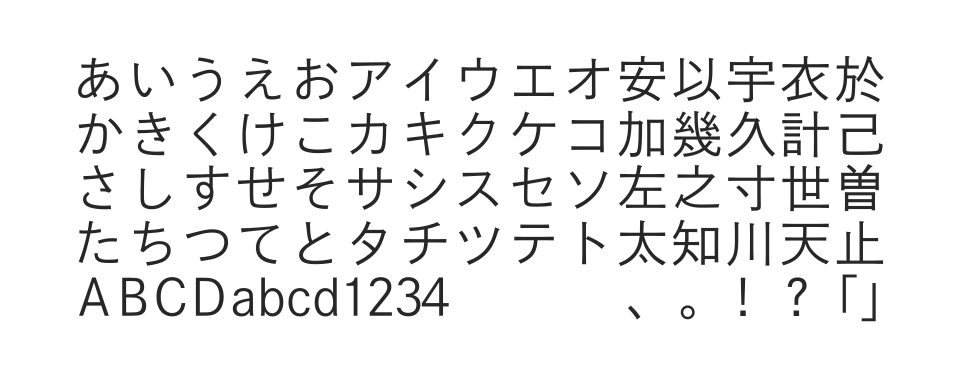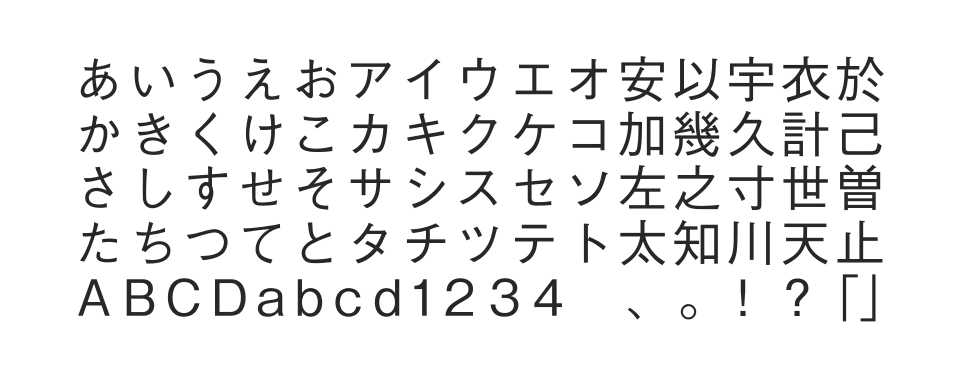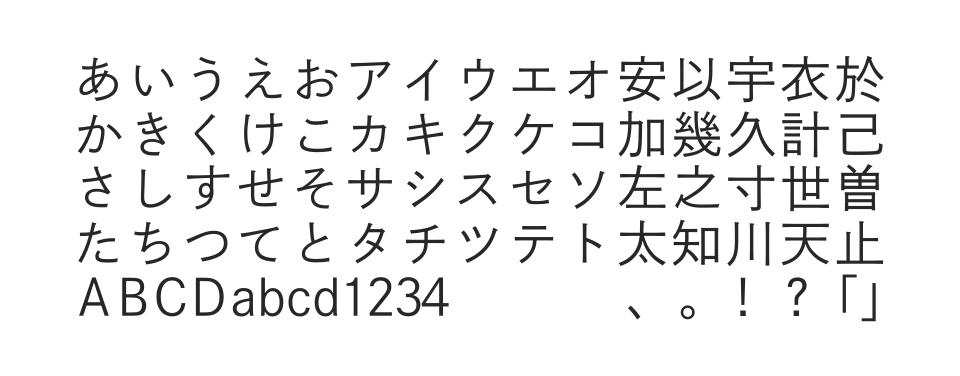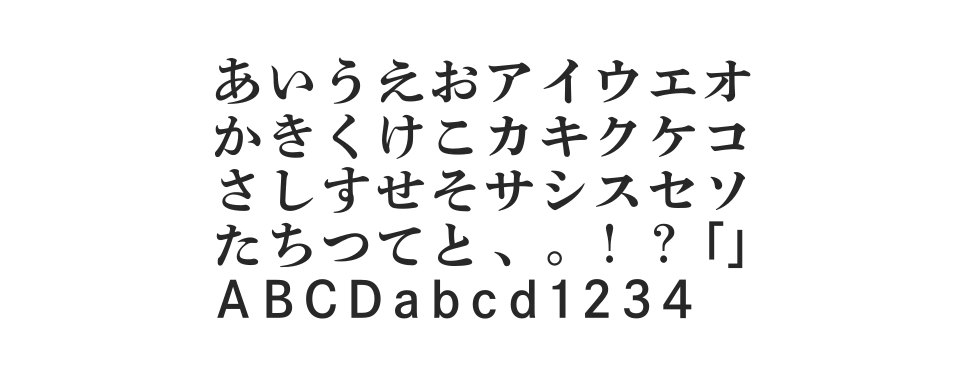
大日本印刷オリジナルのアンチック体を復刻した書体。ゴシック体と並べても違和感がないよう設計され、手の動きを感じさせる重厚感のある文字が特徴的です。
クラシックな印象を持つゴシック体。秀英明朝ののびのびとした骨格を活かし、フトコロの締まったかなが特に縦組みで効果を発揮する落ち着きのある書体です。
長く愛される伝統的なゴシック体でDTPの黎明期を支えた基本書体。オーソドックスな字形と適度な太さで可読性が高く、雑誌本文やキャプションに最適です。
秀英明朝とマッチするオーソドックスなゴシック体。大ぶりで手書き字形に近いかなが親しみやすく、短文や見出しでさりげない存在感を発揮します。
大日本印刷が100年以上開発を続けてきた伝統的な明朝体。秀英体独特の連綿を持ち、目に優しい黒みと落ち着いた雰囲気が特長の本文用書体です。
活版印刷の風合いを再現したにじみ効果を加えたかな書体。秀英四号明朝を復刻し、画線の先端に適度な丸みを持たせたクラシックな印象の書体です。
秀英アンチック体をベースに活版印刷のインクのにじみを再現した書体。アンチック体特有の表情に活版印刷の風合いが加わった独特な書体。
秀英角ゴシック銀をベースに活版印刷のインクのにじみを再現。秀英明朝の骨格を活かしたクラシックな印象で明朝と同じように長い文章にも適している。